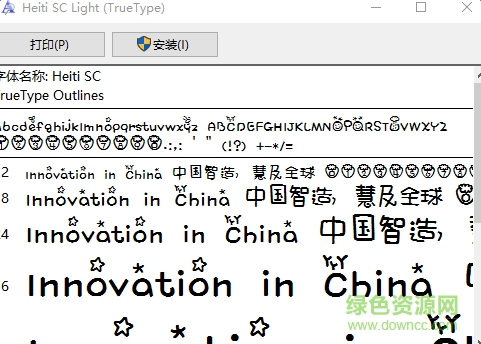
雅芳草莓餅字體是一款很有個(gè)性的電腦藝術(shù)字體,這款字體寫(xiě)出來(lái)的字是很好看的,不僅很活潑還有很多小裝飾品,所以看著特別好看,喜歡這款字體的朋友可以來(lái)綠色資源網(wǎng)下載。
雅芳草莓餅字體真的是一款很不錯(cuò)的電腦字體,寫(xiě)出來(lái)的字是很美的,而且實(shí)用性強(qiáng),特別是用于藝術(shù)方面是很合適的,歡迎有需要的朋友來(lái)綠色資源網(wǎng)下載。